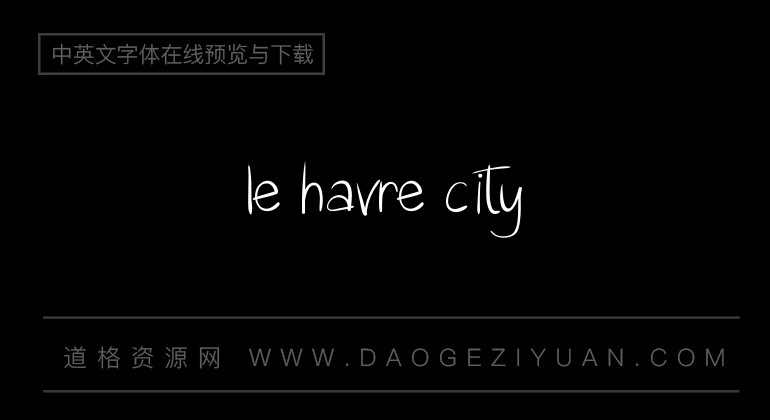
Le Havre City字体是一款现代简洁的英文字体,它具有轻松、简洁和现代感的特点。字体的每一个字母都是精心设计的,使用它可以使文字显得更加精致和简洁。Le Havre City字体也可以用于商业用途,可以用于标志、标语、书籍、杂志和网站等。它可以让文字更加有吸引力,让你的设计更加精致。内容介绍
Le Havre City是一款非常不错的手写艺术字体,具有很好的视觉感,适合于文化类的宣传设计、商业类品牌的广告和产品包装设计以及个性化文字排版等较多场景。